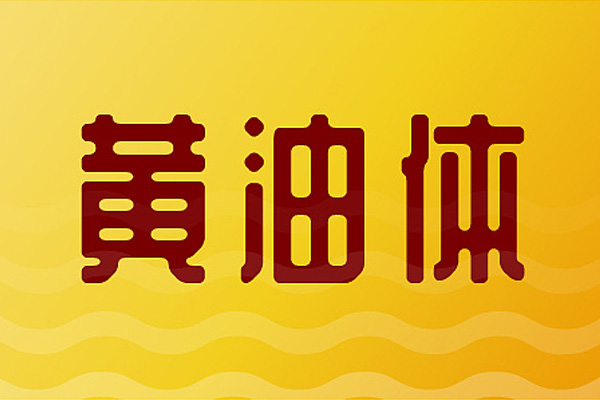
站酷庆科黄油体
字体设计师郑庆科创作了一款名为站酷庆科黄油体的字体。这款字体非常独特,它的每一个直角都被巧妙地处理成了半径为4pt的圆角,呈现出非常圆润的风格。
在创作过程中,设计师非常注重笔划的简化和不省略。每一个笔划都尽量保持垂直角度,使得字体更加简洁易读。此外,字体部首的右下角均为45°缺角,这一设计提高了字体的视觉中心,有效避免了字体笔划交叉造成的阅读困难。
总的来说,站酷庆科黄油体是一款字型创新、线条圆润、简洁易读的字体,具有非常高的实用性和观赏性。无论是用于文本排版还是创意设计,都能展现出其独特的魅力。